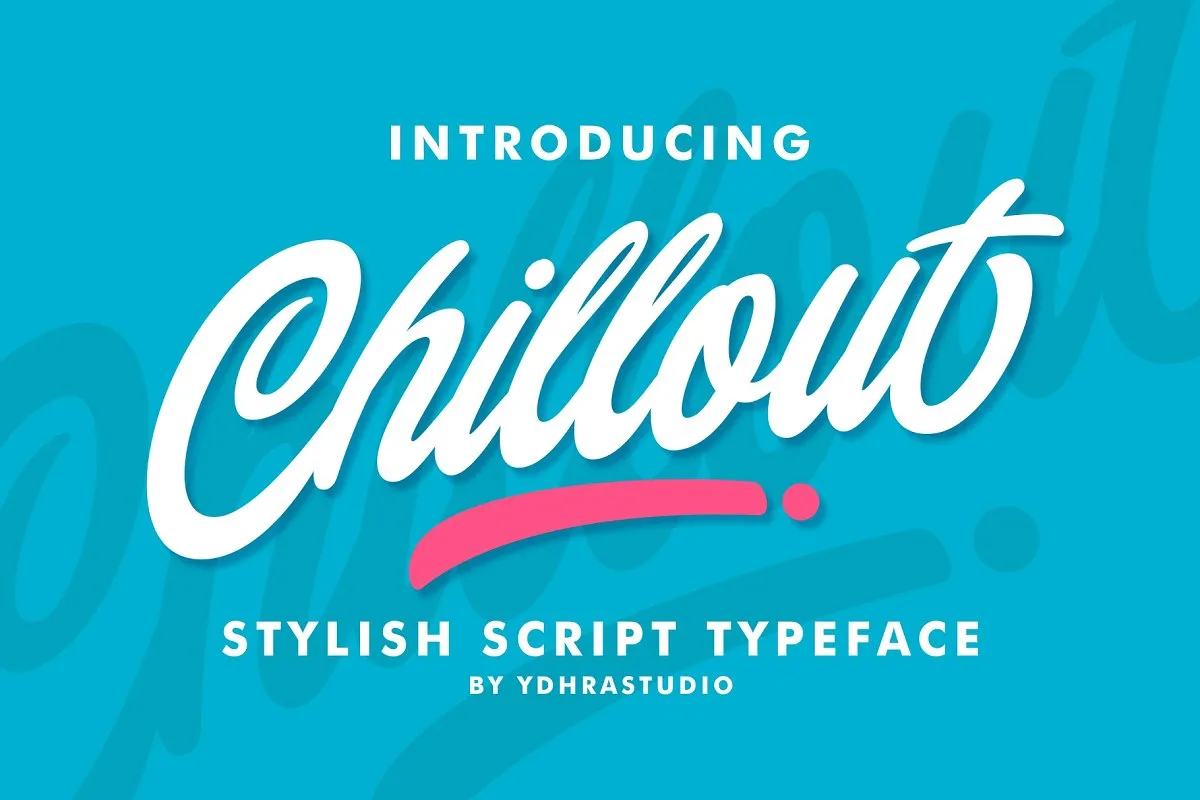
Chillout Script Font – Download Grátis
Chillout Script Font é uma opção perfeita para quem busca uma tipografia com um ar descontraído e inspirador. Inspirada nos traços vigorosos e vibrantes do desenho a mão, essa fonte script é ideal para qualquer projeto que busque um toque de criatividade e sofisticação. Seja para criar logotipos, design de marca, arte digital, letras na internet ou até mesmo para publicações impressas como fita adesiva ou revistas, Chillout Typeface oferece a perfeita mistura de simplicidade e elegância que você precisa. Com uma disposição naturalmente fluida e arredondada, esta fonte é perfeitamente adaptável a várias aplicações gráficas. Suas linhas elegantes e suas cores vibrantes criam um visual inspirador, adequado para qualquer tipo de projeto que deseje exibir um toque descontraído e alegre sem perder o respeito ao trabalho. Este é o ideal para aqueles que buscam uma fonte script moderna e divertida, perfeita para projetos que exigem estilo e criatividade.